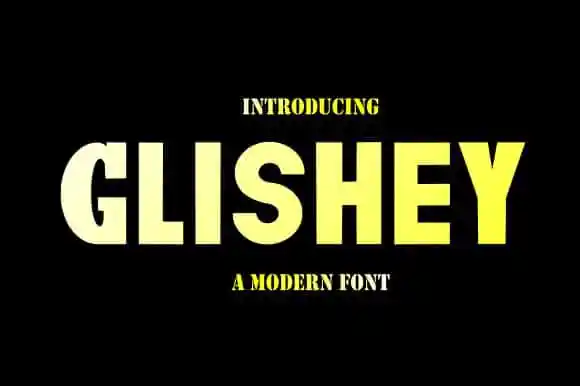
Glishey Sans Serif Font – Download Grátis
Introduzimos a Glishey Sans Serif Font, uma tipografia sem traços que oferece alternativas elegantes para dar destaque ao seu projeto. Esta tipografia será perfeita para logomarca, headlines, cartazes, marca e muito mais. Muitos caracteres em maiúsculas e minúsculas têm alternativas que você pode usar para dar um toque de elegância nos seus textos. Desenvolvida pelo designer Teguh Pranata no site 99designs, a Glishey Sans Serif é uma fonte de exibição moderna e assustadoramente colorida. Ela combina uma forte presença visual com um ar levemente descontraído, tornando-a perfeita para uma variedade extensa de projetos gráficos! Não importa o tema do projeto, essa font irá destacar suas ideias criativas de maneira surpreendente e inovadora.